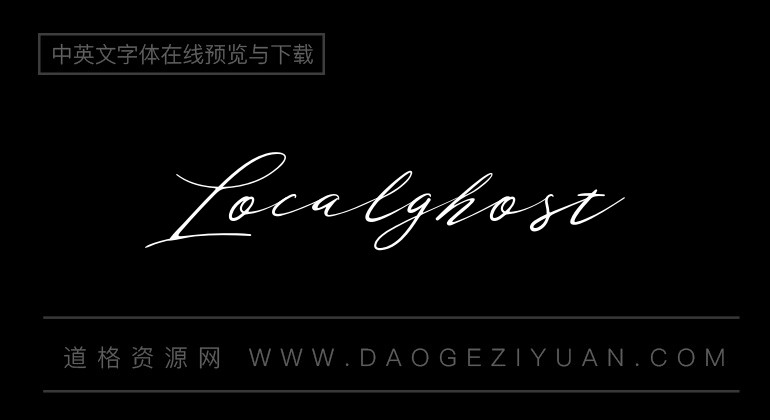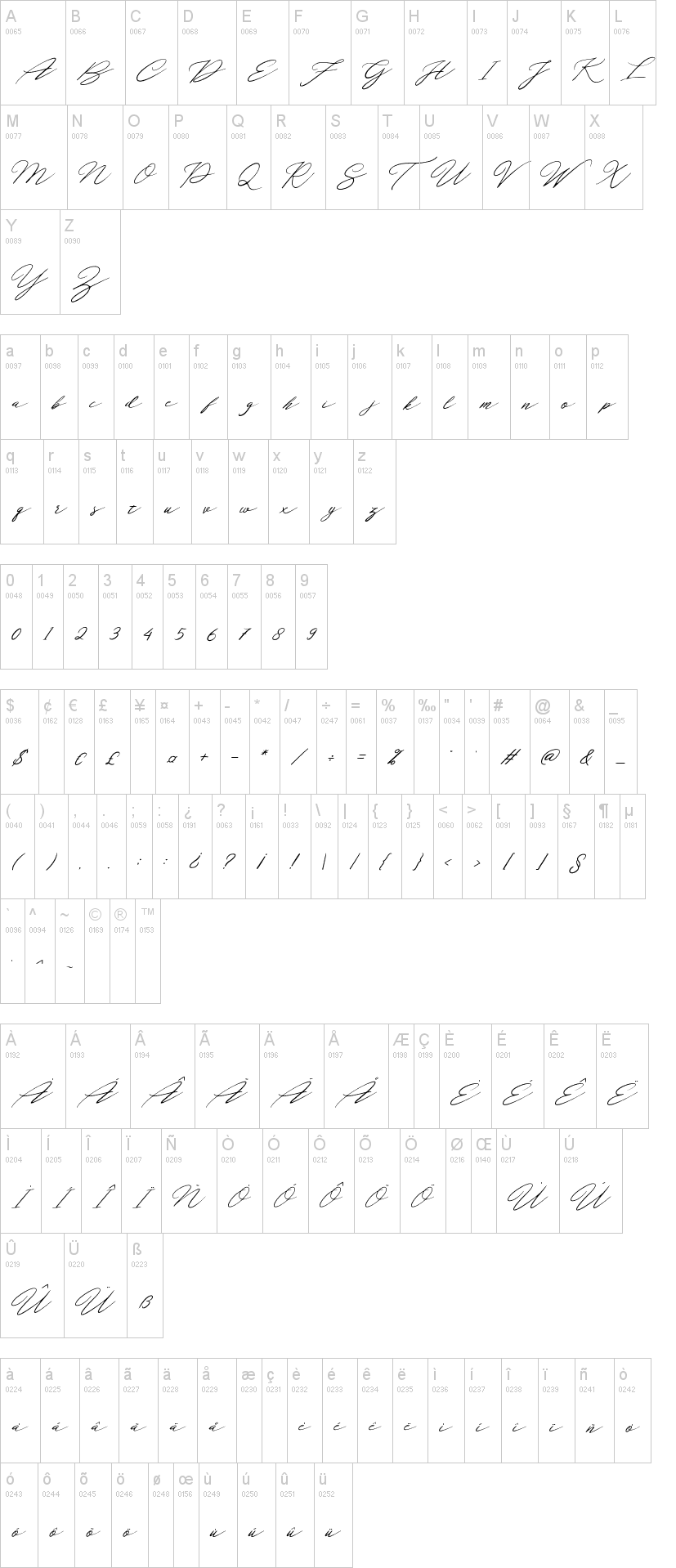
Localghost
Localghost是一款简洁、现代化的字体,由著名设计师Oleg Zhuravlev设计。它具有清晰的轮廓,精致的笔画,灵活的细节,可以满足现代设计的需求。它有多种字体,包括多种字重,可以满足不同的设计需求。Localghost字体的特点是其易读性,使用起来非常方便,可以用于各种应用,如网页、报纸、书籍、广告等。
Localghost是一款非常不错的手写艺术字体,具有很好的视觉感,适合于文化类的宣传设计、商业类品牌的广告和产品包装设计以及个性化文字排版等较多场景。
Localghost字符映射图